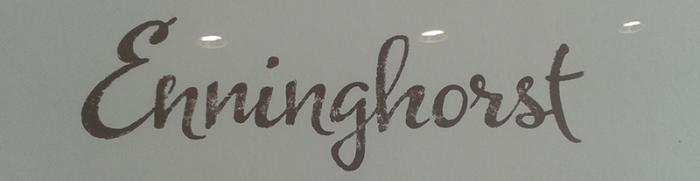
Hilfe!!! Welche Schrift ist das?
ich suche verzweifelt nach folgender Schrift... Das die Typo leicht abgewandelt wurde ist mir klar, ich weis aus eigener Quelle dass sie nicht selbst gezeichnet ist! Ich hoffe ihr könnt mir helfen und mir verraten um welche Schrift es sich hier handelt!
auf die schnelle würde ich sagen das die 3 verschieden n die alternativen zeichen sind.
auch das andere h, r, s und t aus dem original findet man da. nur der übergang vom E (welches auch etwas schräger steht) zum n ist evtl. handgemacht.